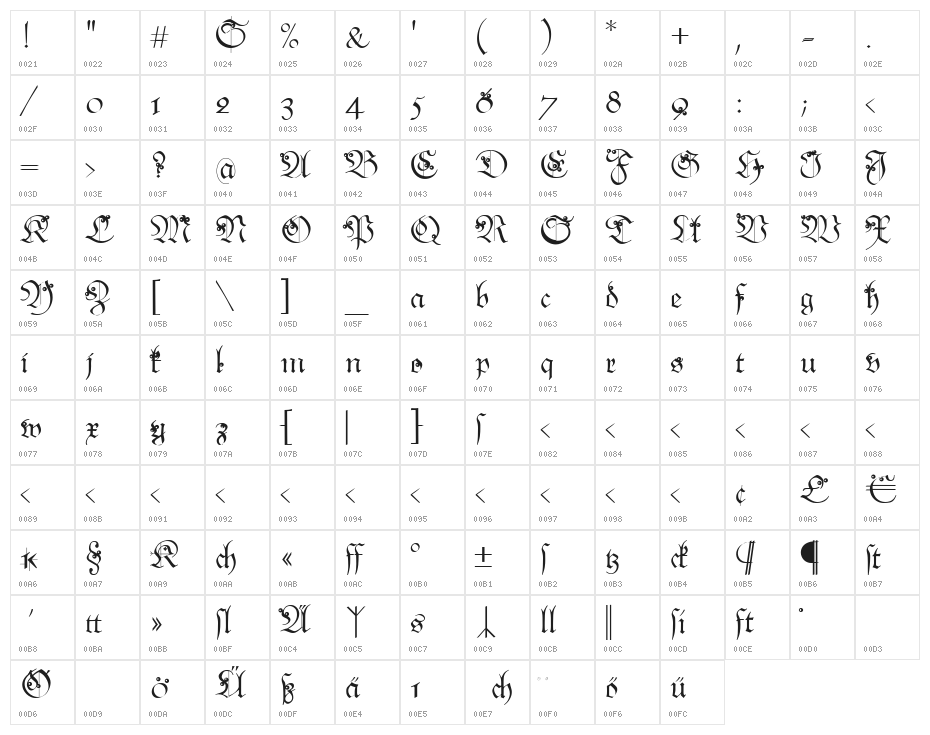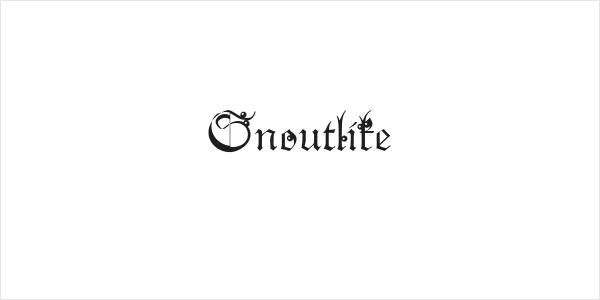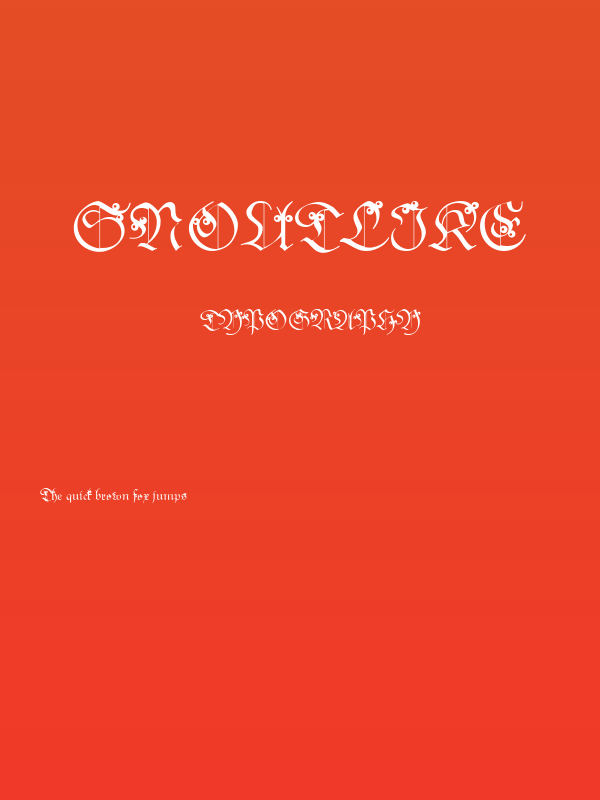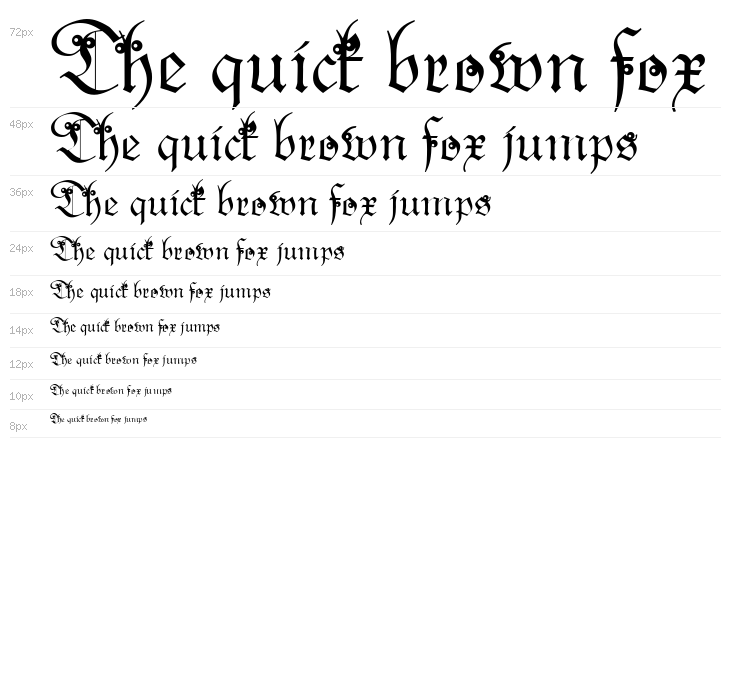
Snoutlike Font
| Caso d'uso | Logos, Headlines, Decorative text |
| Progetti proposti | Suitable for historical documents, wedding invitations, book covers, and branding that requires a classic touch. |